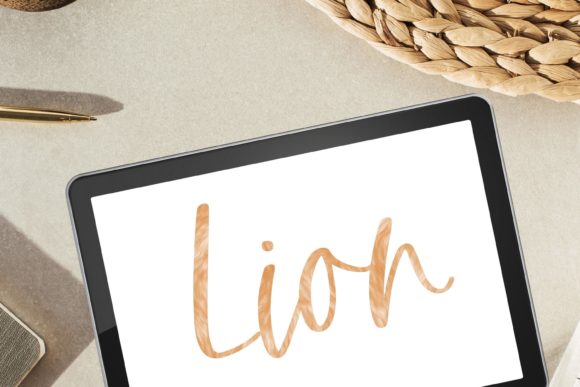
Lion Procreate Brush for Hand Lettering
สร้างขึ้นอย่างแม่นยำ Lion Procreate Brush for Hand Lettering ให้เวกเตอร์ที่สะอาด พิมพ์ตัวอักษรที่ราบรื่น และใบอนุญาตเชิงพาณิชย์เพื่อความสบายใจ